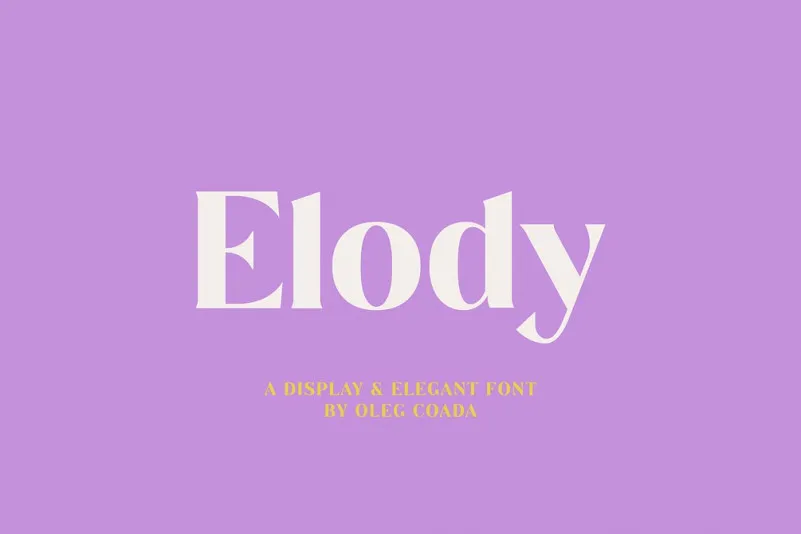
A fonte Elody é ideal para quem busca uma serif que se destaca pela sua facilidade na leitura. Suas linhas suaves e ângulos retos permitem criar um amplo espectro de expressões nos seus projetos, seja no design editorial ou em materiais interativos. Com a combinação perfeita entre os detalhes finos dos caracteres serifados e o encorpamento das letras, Elody oferece uma escolha vasta para qualquer projeto que necessite de elegância e sofisticação. Essencialmente versátil, ela é especialmente propensa a criar um ar de seriedade, ao mesmo tempo que pode adicionar um toque atraente e suave às suas criações. Seja você designer gráfico ou escritor, Elody tem o poder de transformar seus materiais em algo único e envolvente, fazendo parte de uma coleção de fonts únicas e sofisticadas na categoria serif da 99designs.